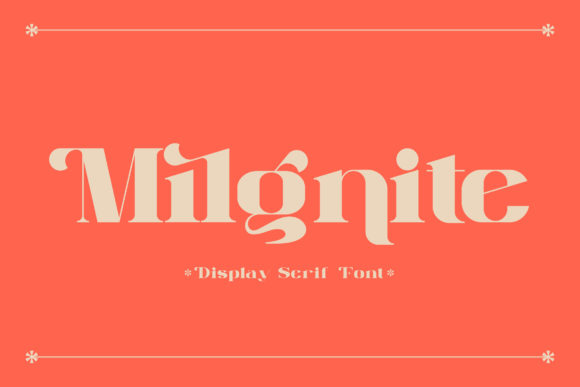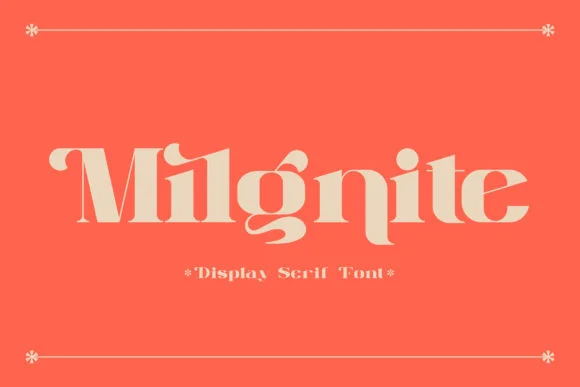
Название: Milgnite Font (2022)
Milgnite - это современный классический шрифт с засечками, обладающий уникальным стилем и восхитительным внешним видом.
Этот шрифт идеально подходит для элегантного и роскошного логотипа, дизайна названия книги или фильма, модного бренда, журнала, одежды, надписей, цитат и многого другого.